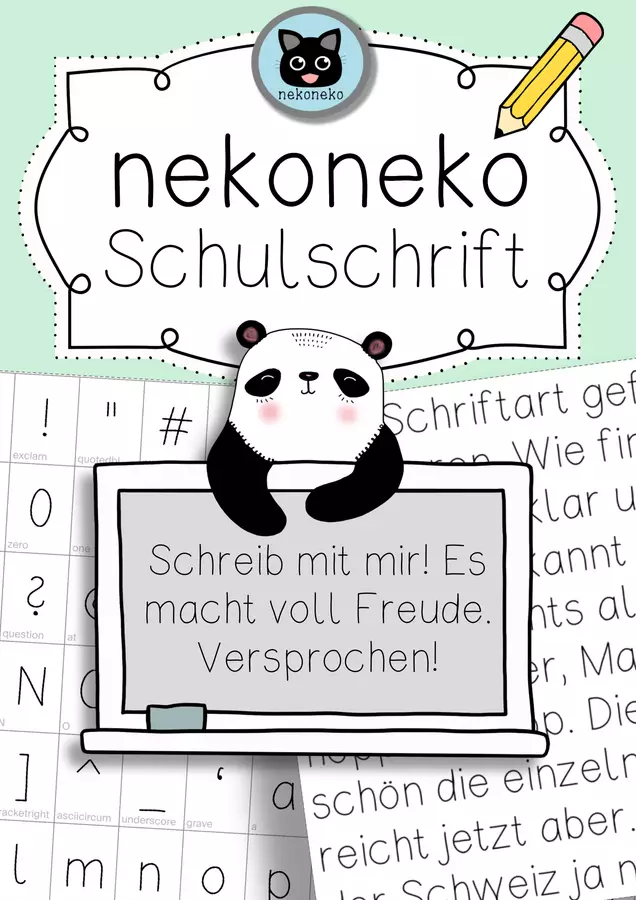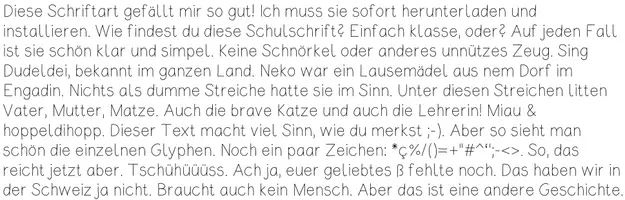
Ich hatte so Lust, eine klare, simple Schulschrift zu zeichnen. Hier siehst du meine neueste Font, die du sowohl privat als auch kommerziell im Bildungsbereich nutzen darfst. Bitte verlinke bei kommerzieller Nutzung immer meinen Shop: https://nekonekogrundschule.com/ .
Ich hoffe, die nekoneko Schulschrift - Font gefällt dir :)